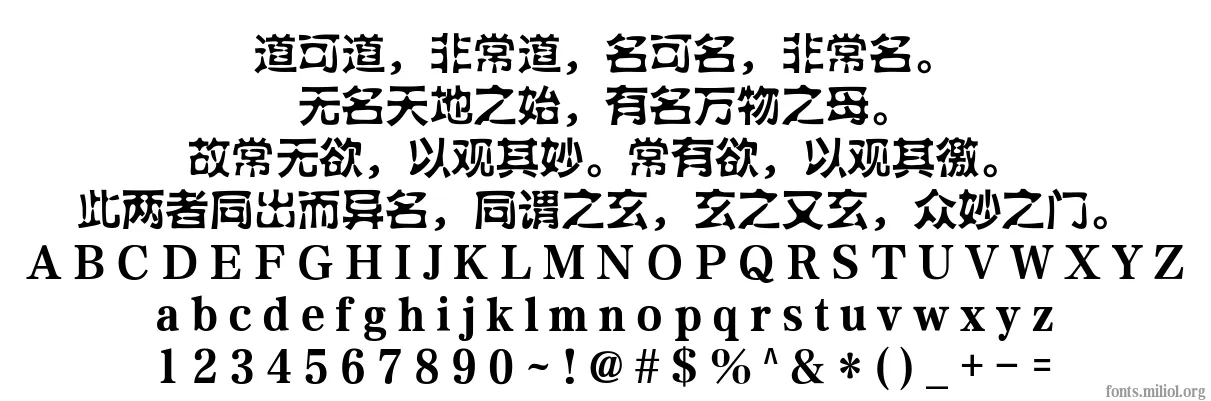
方正水黑_GBK(FZShuiHei-M21)是一款由方正字库设计的中文黑体字体,属于GBK编码字符集,能够支持简体、繁体及日韩汉字等多语种显示。其设计风格融合了传统黑体的稳重与现代无衬线字体的简洁,笔画干净利落,结构匀称,尤其适合标题、广告、屏幕显示等需要醒目效果的场景。
该字体的名称中“水黑”二字暗示了其流畅如水的笔画特征,横竖转折处带有微妙弧度,既保留了黑体的力量感,又增添了一丝柔和气息。作为GBK编码字体,它覆盖了超过两万个汉字字符,兼容性广泛,可满足出版、印刷、数字媒体等多领域需求。FZSHHK--GBK1-0为其内部版本标识,体现了方正字库对字体细节的标准化把控。
在视觉呈现上,方正水黑_GBK的辨识度较高,中宫开阔,字面率适中,小字号下仍能保持清晰阅读体验。其规整而不失灵动的气质,使其成为品牌宣传、包装设计、UI界面的优选字体之一,展现了中文黑体字在当代设计中的多元可能性。